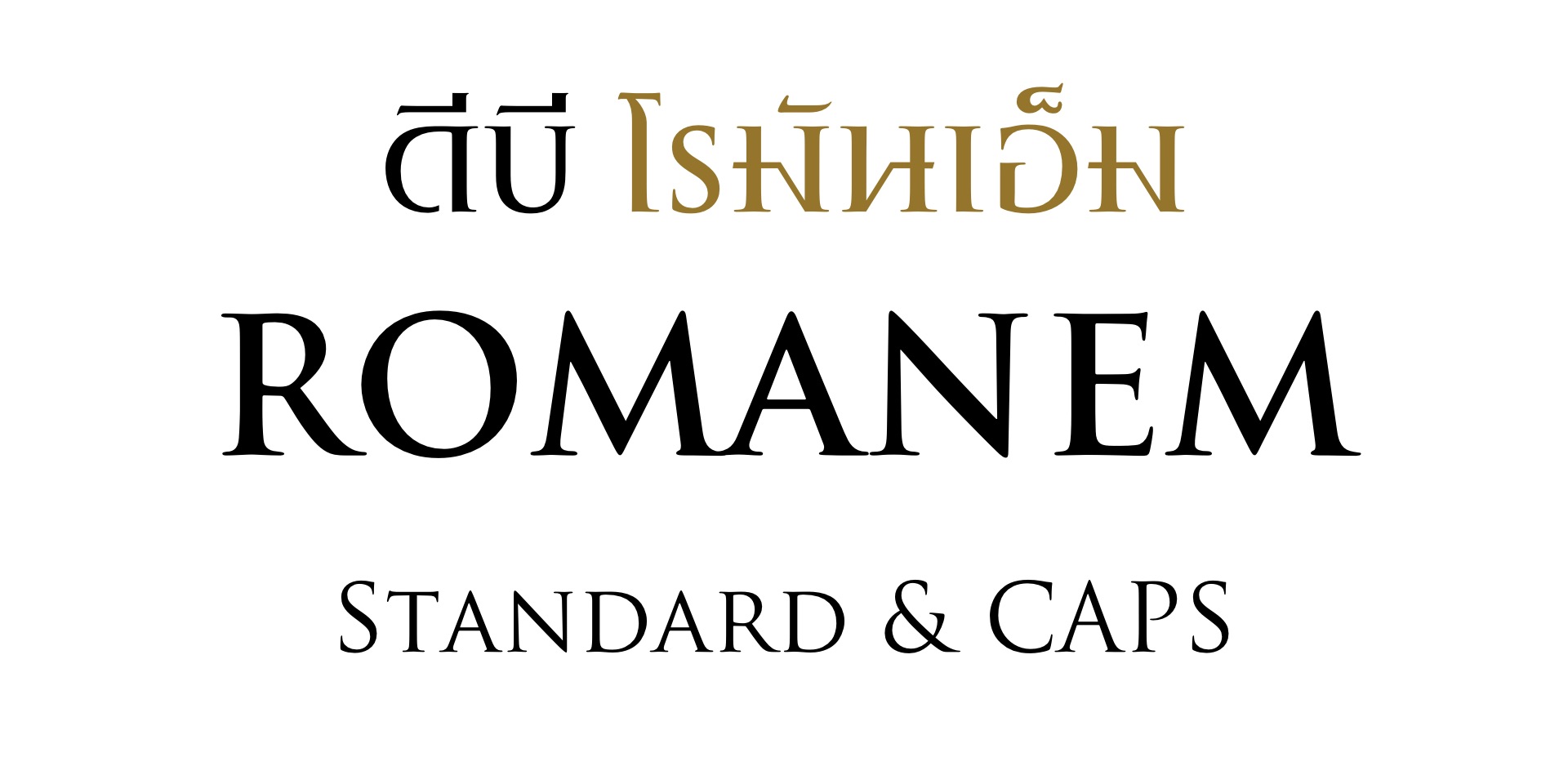
DB Romanem
ดีบี โรมันเอ็ม
DB RomanEm ฟอนต์ไทยเสมือนอักษรที่ถือว่างดงามที่สุดในยุคจักรวรรดิ์โรมัน (ROMAN EMPIRE) เรื่องอำนาจ เป็นตัวสลักหินบนฐาน 'เสาหิน ทราจัน' ที่สร้างขึ้นในปี ค.ศ. 113 ทว่ายังคงความสง่างาม เป็นอมตะมาจนถึงทุกวันนี้
ปัจจุบัน ฟอนต์สไตล์ ทราจัน ยังเป็นที่นิยมใช้กันมาก สาเหตุเพราะให้สุ้มเสียงกว้าง, จากไพเราะงดงาม ไปจนถึงก้องกังวานน่าเกรงขาม